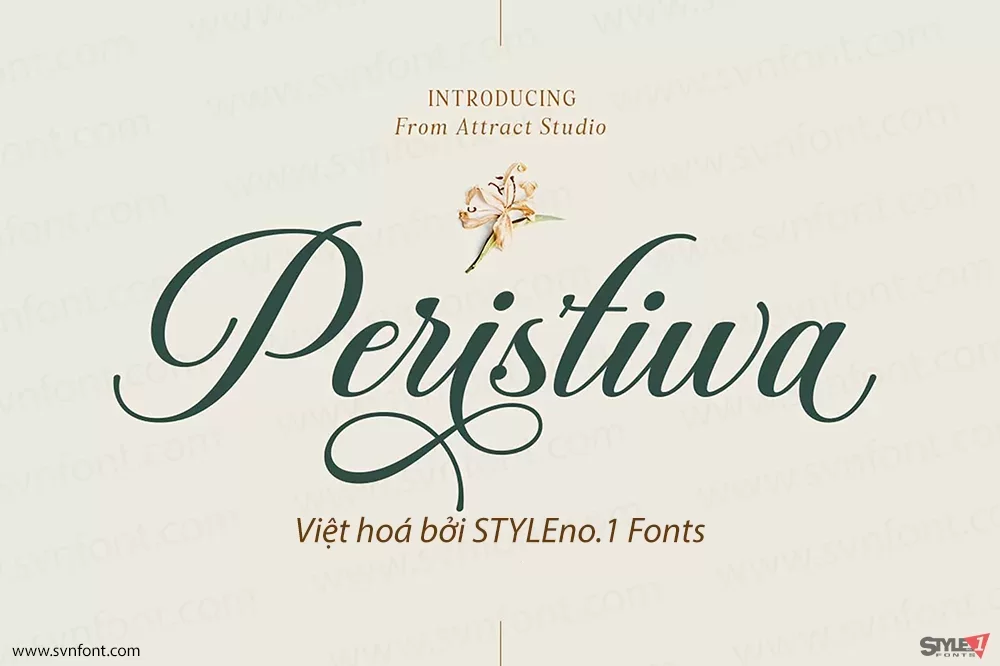
Font chữ Hearth mang vẻ đẹp mềm mại, thanh thoát, với các nét chữ uốn lượn nhẹ nhàng, tạo cảm giác lãng mạn và tinh tế. Những nét chữ cách điệu hình trái tim ở đầu và đuôi chữ làm nổi bật sự ấm áp và yêu thương, rất phù hợp cho các dịp đặc biệt như Ngày Phụ nữ Việt Nam 20/10. Font chữ này có thể được sử dụng để thiết kế thiệp chúc mừng, bìa thư, hoặc các ấn phẩm tôn vinh phái đẹp, góp phần truyền tải những thông điệp ý nghĩa và cảm xúc chân thành.
DVN Alure là một kiểu chữ serif mang phong cách thanh lịch và thời trang, nổi bật với sự tương phản mạnh giữa nét thanh và nét đậm, những đường cong mềm mại cùng các chi tiết chữ mang tính biểu cảm cao. Font tạo cảm giác sang trọng, tinh tế nhưng vẫn có cá tính riêng, đặc biệt phù hợp với thiết kế editorial, thời trang, beauty, branding, poster và tiêu đề nổi bật.
Liveya Script là một font chữ script mang vẻ đẹp tinh tế và lãng mạn, với các đường nét uốn lượn mềm mại, tạo cảm giác liền mạch và duyên dáng. Đặc biệt, các điểm nhấn hình trái tim được khéo léo lồng ghép vào những nét nối và chi tiết của chữ, làm nổi bật phong cách thanh thoát và đầy nữ tính. Kiểu chữ này không chỉ gây ấn tượng bởi sự trang nhã mà còn mang lại cảm giác thân thiện và gần gũi.
DVN – Varigo là font serif mang phong cách hiện đại, kết hợp giữa những đường nét thanh mảnh và độ tương phản cao, tạo nên vẻ đẹp sang trọng, tinh tế và đầy cuốn hút. Bộ font được thiết kế để phù hợp với các dự án cần sự cao cấp, thời trang và chuyên nghiệp, đồng thời vẫn đảm bảo khả năng đọc tốt ở cả tiêu đề lẫn nội dung ngắn.
DVN Lively Việt hóa là một font chữ script mang phong cách vui tươi và năng động, được thiết kế với những đường nét mềm mại nhưng đầy đặn, tạo nên sự hài hòa giữa sự thanh lịch và nổi bật. Font chữ này đặc biệt ấn tượng với các ký tự tròn trịa, thể hiện sự sáng tạo và linh hoạt, phù hợp cho những thiết kế cần sự thu hút ngay từ cái nhìn đầu tiên.
Font chữ Arena mang đến vẻ đẹp tinh tế, pha trộn giữa phong cách cổ điển và hiện đại. Với các nét đậm, chắc chắn, font chữ này thể hiện sự mạnh mẽ nhưng vẫn giữ được sự mềm mại và thanh thoát nhờ các đường cong mượt mà. Arena phù hợp cho các dự án thiết kế liên quan đến thương hiệu cao cấp, biên tập sách, và các ấn phẩm quảng cáo, nơi cần sự sang trọng và sự chuyên nghiệp. Phần khoảng cách giữa các chữ cái được tối ưu giúp tăng khả năng đọc, dù là ở cỡ chữ lớn hay nhỏ. Arena dễ dàng ứng dụng trong nhiều ngữ cảnh khác nhau, từ thiết kế đồ họa đến truyền thông số, mang đến sự thu hút và dễ nhận diện cho người xem.
Philosopher là một font chữ sans-serif hiện đại, được biết đến với sự kết hợp giữa sự đơn giản và phong cách. Thiết kế bởi Jovanny Lemonad, font chữ này nổi bật với các đường nét mềm mại, uốn lượn nhẹ nhàng, mang lại cảm giác thanh thoát và dễ chịu cho người nhìn.
DVN Hải Vân là một font chữ mang đậm chất nữ tính, với những đường nét uốn lượn tinh tế và mềm mại như những gợn sóng trên mặt biển. Các ký tự của font có độ dày vừa phải, tạo nên cảm giác chắc chắn nhưng không mất đi sự thanh thoát, nhẹ nhàng. Điểm nhấn của DVN Hải Vân nằm ở những nét cong mềm mịn, mang đến phong cách quyến rũ và đầy sức sống.
Font chữ này lý tưởng cho các thiết kế nữ tính, từ thiệp mời đám cưới, logo thương hiệu thời trang, đến bìa sách và tạp chí. Ngoài ra, Sophia Beauty còn phù hợp với các dự án sáng tạo như thiết kế bao bì, poster nghệ thuật, và trang web cá nhân. Sự tinh tế và linh hoạt của Sophia Beauty giúp nó dễ dàng tương thích với nhiều phong cách thiết kế khác nhau, mang lại vẻ đẹp độc đáo và cuốn hút cho bất kỳ dự án nào.
DVN Astera là một font chữ Serif hiện đại, tinh tế được Việt hóa hoàn chỉnh, mang đến sự hoàn hảo cho các thiết kế cao cấp, sang trọng. Với các đường nét thanh mảnh, mềm mại kết hợp với các ligature độc đáo, DVN Astera tạo nên một phong cách chữ viết trang nhã và lịch lãm. Các ký tự của DVN Astera có sự cân đối hài hòa, vừa mang nét cổ điển của Serif vừa có sự phá cách của thời đại mới, giúp dễ dàng thu hút ánh nhìn. Font chữ này không chỉ nổi bật trong các thiết kế thương hiệu, logo, mà còn phù hợp cho các ấn phẩm quảng cáo, bao bì sản phẩm, và thiệp mời. Với sự đa dạng trong ứng dụng và tính thẩm mỹ cao, DVN Astera là lựa chọn lý tưởng cho các thương hiệu mong muốn truyền tải thông điệp sang trọng và đẳng cấp.
Peristiwa Script là một phông chữ thư pháp lấy cảm hứng từ sự cổ điển và trang nhã, đầy đủ tính năng với nhiều ký tự thay thế và các tính năng OpenType. Nét viết tay hoàn hảo với góc vuông đậm là sự lựa chọn hoàn hảo cho biểu tượng, thiệp mời đám cưới, trang web hiện đại, thiệp chúc mừng và hơn thế nữa!
DVN Hearth Việt hóa - Font chữ trái tim rất hợp cho ngày 20 tháng 10
Font chữ Hearth mang vẻ đẹp mềm mại, thanh thoát, với các nét chữ uốn lượn nhẹ nhàng, tạo cảm giác lãng mạn và tinh tế. Những nét chữ cách điệu hình trái tim ở đầu và đuôi chữ làm nổi bật sự ấm áp và yêu thương, rất phù hợp cho các dịp đặc biệt như Ngày Phụ nữ Việt Nam 20/10. Font chữ này có thể được sử dụng để thiết kế thiệp chúc mừng, bìa thư, hoặc các ấn phẩm tôn vinh phái đẹp, góp phần truyền tải những thông điệp ý nghĩa và cảm xúc chân thành.
DVN Alure tiếng Việt
DVN Alure là một kiểu chữ serif mang phong cách thanh lịch và thời trang, nổi bật với sự tương phản mạnh giữa nét thanh và nét đậm, những đường cong mềm mại cùng các chi tiết chữ mang tính biểu cảm cao. Font tạo cảm giác sang trọng, tinh tế nhưng vẫn có cá tính riêng, đặc biệt phù hợp với thiết kế editorial, thời trang, beauty, branding, poster và tiêu đề nổi bật.
MTD Kiramba
DVN Loveya Script
Liveya Script là một font chữ script mang vẻ đẹp tinh tế và lãng mạn, với các đường nét uốn lượn mềm mại, tạo cảm giác liền mạch và duyên dáng. Đặc biệt, các điểm nhấn hình trái tim được khéo léo lồng ghép vào những nét nối và chi tiết của chữ, làm nổi bật phong cách thanh thoát và đầy nữ tính. Kiểu chữ này không chỉ gây ấn tượng bởi sự trang nhã mà còn mang lại cảm giác thân thiện và gần gũi.
DVN Serene tiếng Việt
DVN Varigo tiếng Việt
DVN – Varigo là font serif mang phong cách hiện đại, kết hợp giữa những đường nét thanh mảnh và độ tương phản cao, tạo nên vẻ đẹp sang trọng, tinh tế và đầy cuốn hút. Bộ font được thiết kế để phù hợp với các dự án cần sự cao cấp, thời trang và chuyên nghiệp, đồng thời vẫn đảm bảo khả năng đọc tốt ở cả tiêu đề lẫn nội dung ngắn.
Sarigo tiếng Việt
DVN Lively Việt hóa
DVN Lively Việt hóa là một font chữ script mang phong cách vui tươi và năng động, được thiết kế với những đường nét mềm mại nhưng đầy đặn, tạo nên sự hài hòa giữa sự thanh lịch và nổi bật. Font chữ này đặc biệt ấn tượng với các ký tự tròn trịa, thể hiện sự sáng tạo và linh hoạt, phù hợp cho những thiết kế cần sự thu hút ngay từ cái nhìn đầu tiên.
DVN ARENA Việt hóa
Font chữ Arena mang đến vẻ đẹp tinh tế, pha trộn giữa phong cách cổ điển và hiện đại. Với các nét đậm, chắc chắn, font chữ này thể hiện sự mạnh mẽ nhưng vẫn giữ được sự mềm mại và thanh thoát nhờ các đường cong mượt mà. Arena phù hợp cho các dự án thiết kế liên quan đến thương hiệu cao cấp, biên tập sách, và các ấn phẩm quảng cáo, nơi cần sự sang trọng và sự chuyên nghiệp. Phần khoảng cách giữa các chữ cái được tối ưu giúp tăng khả năng đọc, dù là ở cỡ chữ lớn hay nhỏ. Arena dễ dàng ứng dụng trong nhiều ngữ cảnh khác nhau, từ thiết kế đồ họa đến truyền thông số, mang đến sự thu hút và dễ nhận diện cho người xem.
Philosopher
Philosopher là một font chữ sans-serif hiện đại, được biết đến với sự kết hợp giữa sự đơn giản và phong cách. Thiết kế bởi Jovanny Lemonad, font chữ này nổi bật với các đường nét mềm mại, uốn lượn nhẹ nhàng, mang lại cảm giác thanh thoát và dễ chịu cho người nhìn.
DVN Hải Vân
DVN Hải Vân là một font chữ mang đậm chất nữ tính, với những đường nét uốn lượn tinh tế và mềm mại như những gợn sóng trên mặt biển. Các ký tự của font có độ dày vừa phải, tạo nên cảm giác chắc chắn nhưng không mất đi sự thanh thoát, nhẹ nhàng. Điểm nhấn của DVN Hải Vân nằm ở những nét cong mềm mịn, mang đến phong cách quyến rũ và đầy sức sống.
DVN Sophia Beauty
Font chữ này lý tưởng cho các thiết kế nữ tính, từ thiệp mời đám cưới, logo thương hiệu thời trang, đến bìa sách và tạp chí. Ngoài ra, Sophia Beauty còn phù hợp với các dự án sáng tạo như thiết kế bao bì, poster nghệ thuật, và trang web cá nhân. Sự tinh tế và linh hoạt của Sophia Beauty giúp nó dễ dàng tương thích với nhiều phong cách thiết kế khác nhau, mang lại vẻ đẹp độc đáo và cuốn hút cho bất kỳ dự án nào.
DVN Astera Việt hóa
DVN Astera là một font chữ Serif hiện đại, tinh tế được Việt hóa hoàn chỉnh, mang đến sự hoàn hảo cho các thiết kế cao cấp, sang trọng. Với các đường nét thanh mảnh, mềm mại kết hợp với các ligature độc đáo, DVN Astera tạo nên một phong cách chữ viết trang nhã và lịch lãm. Các ký tự của DVN Astera có sự cân đối hài hòa, vừa mang nét cổ điển của Serif vừa có sự phá cách của thời đại mới, giúp dễ dàng thu hút ánh nhìn. Font chữ này không chỉ nổi bật trong các thiết kế thương hiệu, logo, mà còn phù hợp cho các ấn phẩm quảng cáo, bao bì sản phẩm, và thiệp mời. Với sự đa dạng trong ứng dụng và tính thẩm mỹ cao, DVN Astera là lựa chọn lý tưởng cho các thương hiệu mong muốn truyền tải thông điệp sang trọng và đẳng cấp.
DVN Elegent Việt hóa
Goldeye Type Việt hóa
SVN Peristiwa Việt hóa
Peristiwa Script là một phông chữ thư pháp lấy cảm hứng từ sự cổ điển và trang nhã, đầy đủ tính năng với nhiều ký tự thay thế và các tính năng OpenType. Nét viết tay hoàn hảo với góc vuông đậm là sự lựa chọn hoàn hảo cho biểu tượng, thiệp mời đám cưới, trang web hiện đại, thiệp chúc mừng và hơn thế nữa!